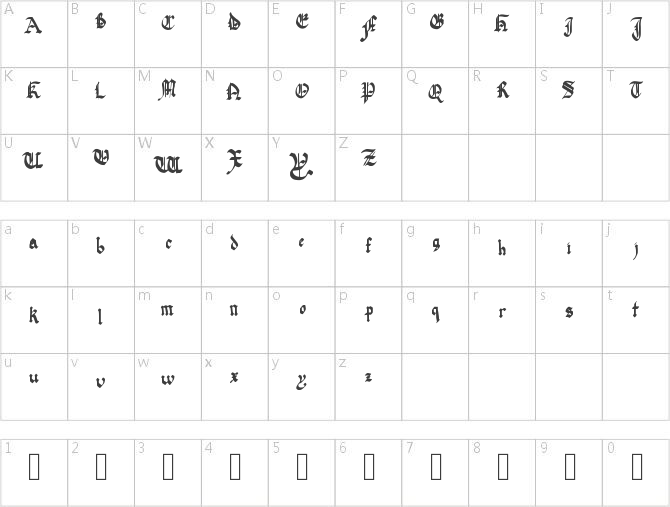
quadrata preciosa 詳情頁
字體名稱: quadrat
quadrata preciosa
quadrata preciosa介紹
quadrata preciosa字體字庫是一款讓人賞心悅目、百看不厭的英文字體,適合各類廣告和產品包裝設計應用,字體大小0.02MB,格式為ttf字體,上傳用戶是yinjun,作者/版權方為未知